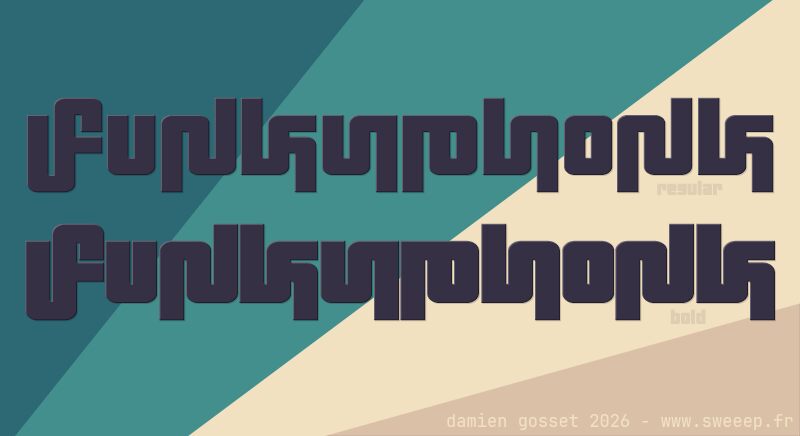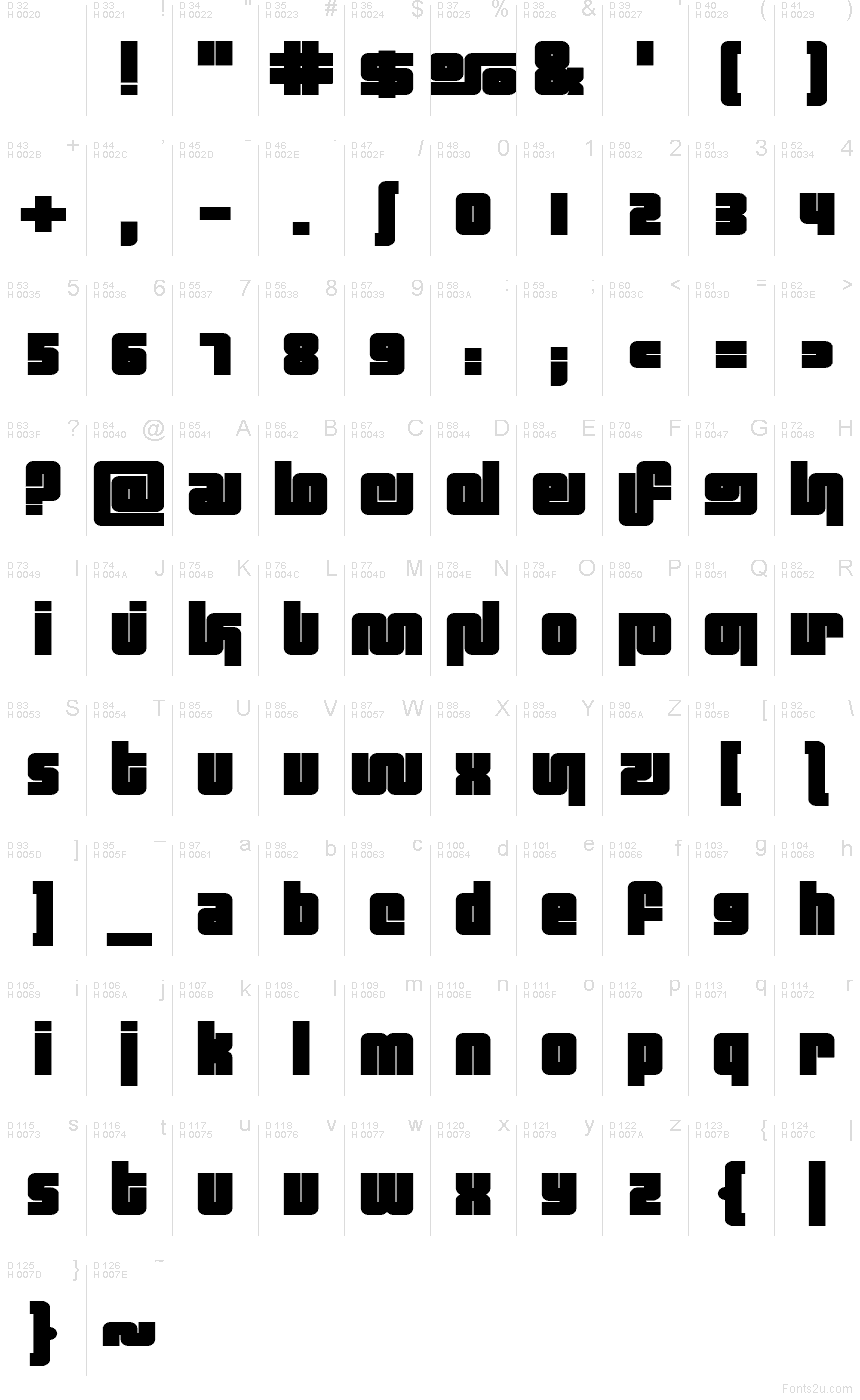
Funkyphonk Bold od Damiena Gosseta je bezplatné groovy display písmo s masivními, těsně uspořádanými tvary a nekompromisním futuristickým nádechem. Široké oblouky se potkávají s hranatými náběhy a tenké vnitřní zářezy vytvářejí v písmenech dráhy připomínající bludiště. Několik liter svými hlubokými záhyby a úzkými otvory připomíná ohnuté trubky či součásti strojů.
Nejlépe se hodí pro publikum spojené s hudbou a nočním životem. Jeho hutná silueta dokáže proměnit obaly alb, klubové plakáty, branding streetwearu i festivalovou grafiku v kompaktní emblémy, zatímco v redakční sazbě mohou tyto zdánlivě oříznuté tvary posloužit jako titulkové nápisy i jako grafické prvky stránky.